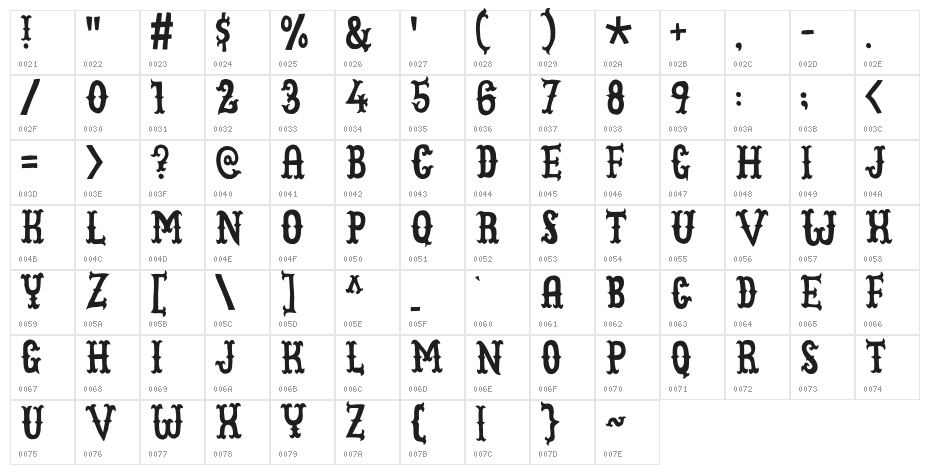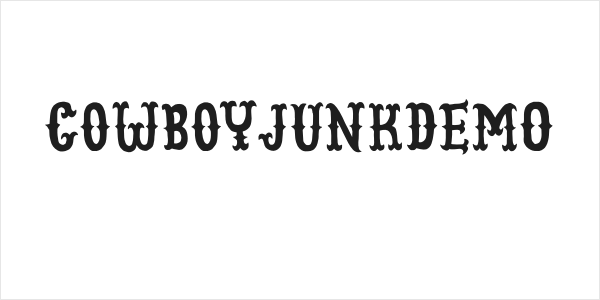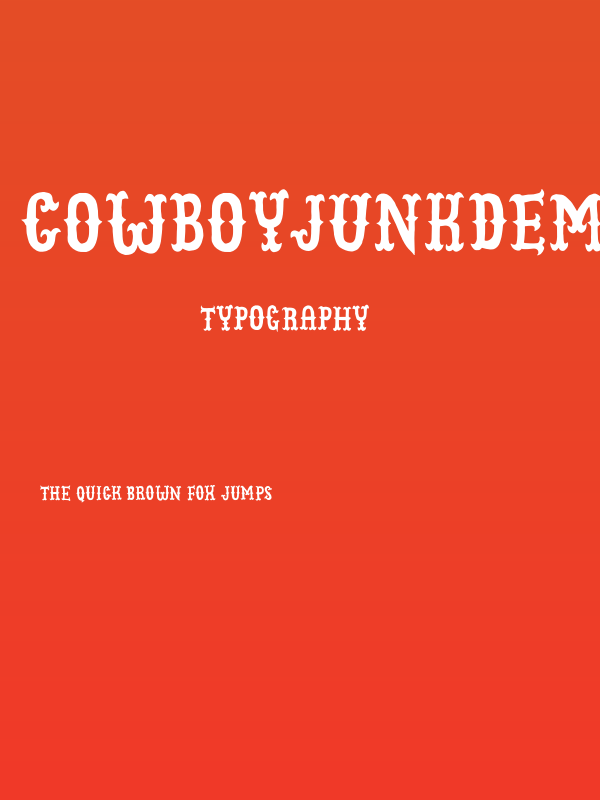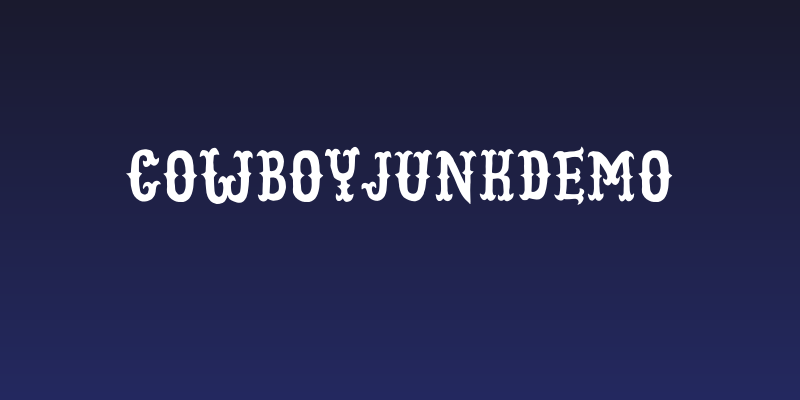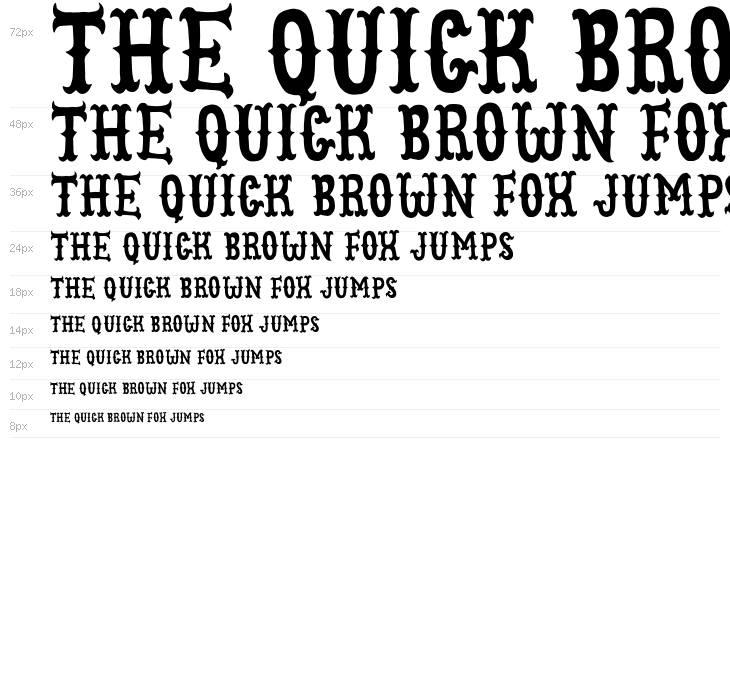
CowboyJunkDEMO Font
✎ Western
| Kategorien | Western |
| Gesamtstil | Vintage |
| Vorgeschlagene Projekte | Ideal for Western-themed posters, event invitations, branding for rustic or vintage products, and any design requiring a bold, eye-catching typeface. |